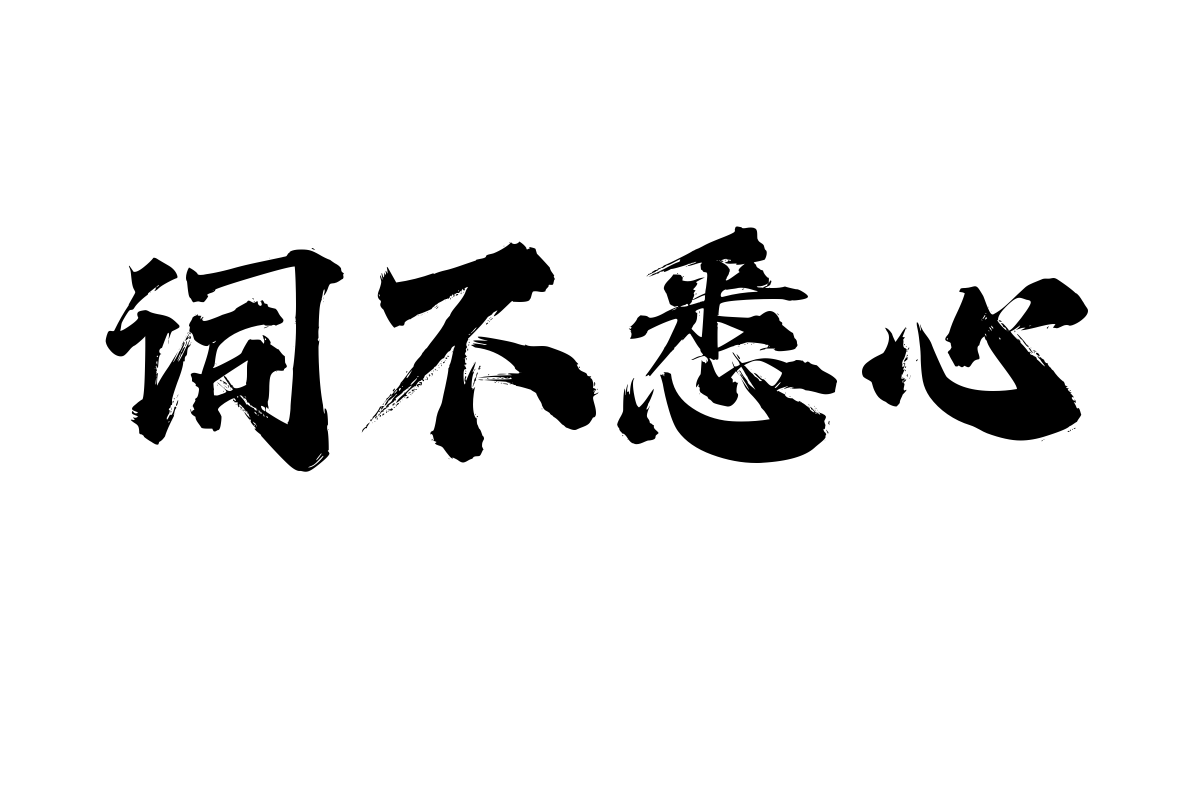
潮字社豪侠手书是一套由潮字社推出的书法字体,包括简体和繁体两个版本。这套字体以其独特的设计风格和优美的线条而受到广泛欢迎。
1. 设计风格:潮字社豪侠手书采用了传统的书法风格,结合了现代的审美观念,使得整体看起来更加时尚、大气。字体结构紧凑,线条流畅,给人一种简洁而又有力量的感觉。
2. 字体特点:这套字体的最大特点是其独特的笔画处理。每个笔画都经过精心的设计,使得整体看起来既有美感又不失力度。同时,字体的间距也经过精心设计,使得整体看起来既紧凑又富有层次感。
3. 适用场景:潮字社豪侠手书适用于各种需要展示书法艺术的场景,如广告设计、产品包装、海报设计等。同时,也适合用于个人电脑、手机等电子设备的显示界面,使得文字更具艺术感。